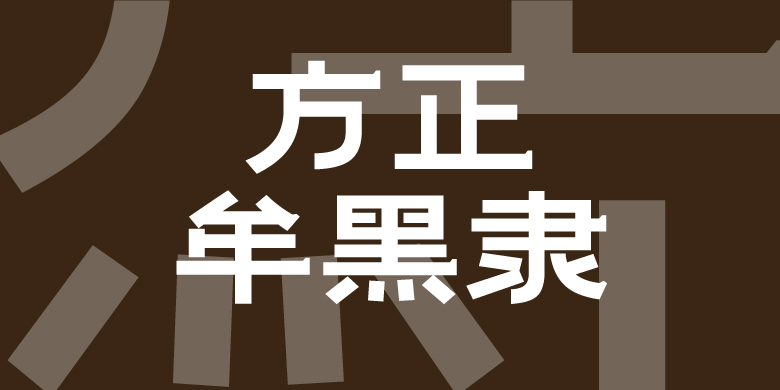
方正牟黑隶
《方正牟黑隶》是《方正字迹-牟氏黑隶体》的设计字形,有简、黑、拙三大特点,类似风格的隶书兴于清代,创作者进一步简化笔形使其更接近当代黑体字,将隶书原有的蚕头燕尾变为直横,收笔处向上形成小三角,笔画整体粗实,字形饱满。这款字体保留了清代隶书的风韵,古意盎然、朴茂沉雄,适用于书刊标题、广告和产品包装设计。